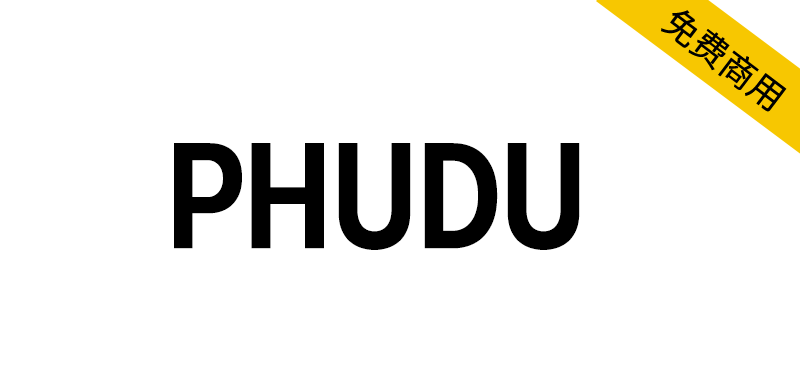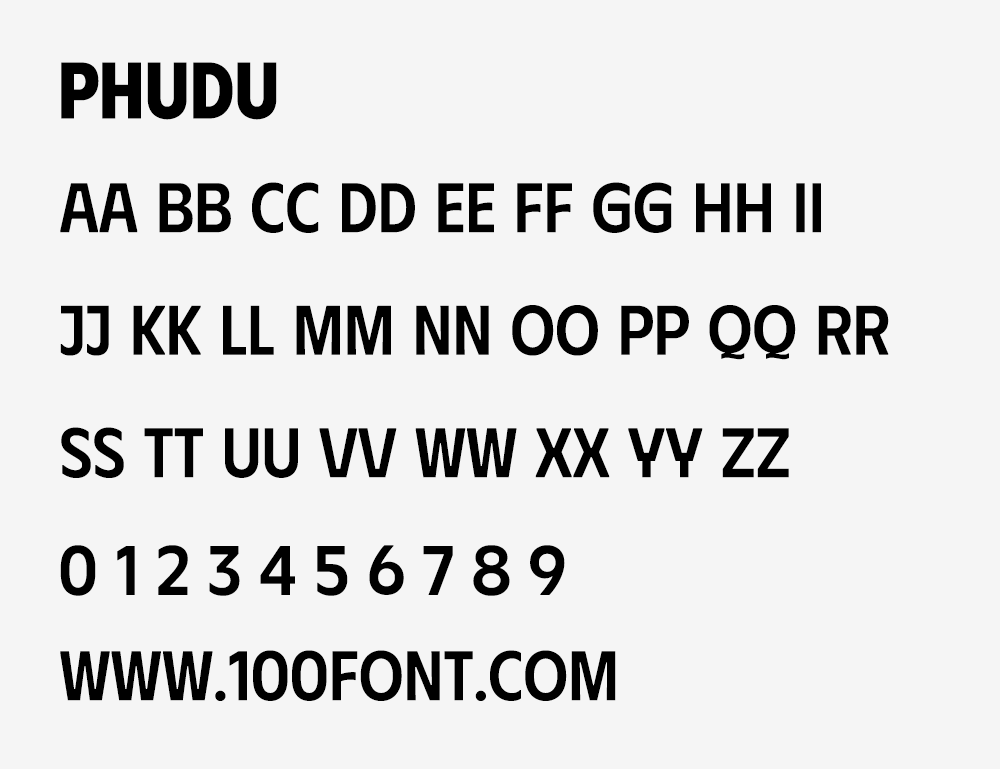
DT Phudu是一种无衬线字体,灵感来自过去越南的手写广告牌。它由从浅色到黑色的5个权重组成,与其他轻量级窄字体相比,它越轻,就越扩展,以提高可读性。有些细节是尖端的,并没有为此目的而变得尖锐。DT Phudu有相同的大写和小写,只使用全大写的信息显示,就像我们越南的广告牌风格。
我为什么要做这种字体?在学习和制作字体的过程中,我一直在思考是什么造就了越南字体。如果我们回到过去,我们可以在广告牌商店看到我们的字体风格,当时艺术家们改编了拉丁字体,然后根据他们的风格添加了标记。其中,大多数都是无衬线的大写字母,用作描述,有时也用作商店名称本身。为了制作一种新的易读易用的字体,我将上面故事中的一些研究与字母混合在一起。我不想只是复兴这些类型,我想改进它们,这样它们就可以适应现代风格,但仍然有“越南人”的灵魂。字体命名为DT Phudu(phục dựng)-越南语中的“复兴”,具有永恒的含义(与名称相反,它可以读作“phúdu”-短暂)。
DT Phudu is a display sans-serif typeface inspired by Vietnamese hand-lettering billboards in the old days. It consists of 5 weights from Light to Black, and the lighter it gets, the extended it becomes, for readability compared to other lightweight narrow typefaces. Some details are cutting-edge and not sharpened for this purpose too. DT Phudu has the same upper and lower-case, with the message of using only ALLCAPS for display purposes just like our Vietnamese billboard styles.
Why I made this typeface? In the process of learning and crafting types, I have always thought about what makes a Vietnamese typeface. If we rewind to the past, we can see our lettering styles on the billboard stores, when the artists adapted Latin typefaces and then added marks based on their styles. Among those, there were mostly all-caps sans-serif types played as descriptions or sometimes the store's names themself. To make a new easy to read and easy-to-get typeface, I mixed some of the research from the story above with letters. I don't want to just revive the types, I want to improve them, so they can fit the modern-day styles but still have "Vietnamese" souls in them. The typeface was named DT Phudu (phục dựng) - "revival" in Vietnamese, and has a meaning of timeless (quite the opposite of the name when it can be read as "phù du" - ephemeral).